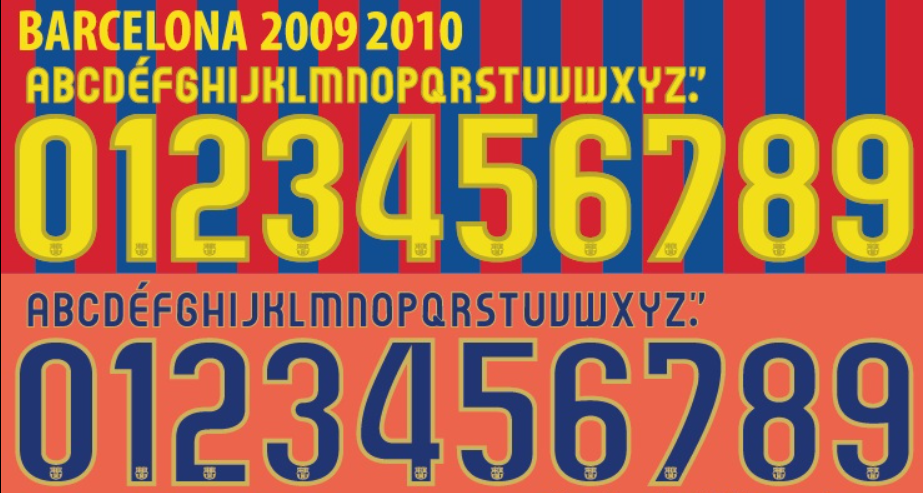
Se existe uma temporada que está gravada na memória de qualquer fã de futebol, é a de 2010/11. Foi o auge do “tiki-taka” de Pep Guardiola, quando o FC Barcelona encantou o mundo. Agora, você pode recriar a magia daquele time histórico com a tipografia oficial utilizada por lendas como Messi, Xavi e Iniesta.
Este arquivo traz a fonte exata desenhada pela Nike para a temporada em que os Culés levantaram a taça da Champions League em Wembley. É um recurso indispensável para colecionadores, designers e personalizadores que buscam fidelidade histórica.
Estilo Visual e Legado
A tipografia criada pela Nike para o ciclo 2010/2011 foge do padrão excessivamente futurista. Ela apresenta um design arredondado, suave e altamente legível, transmitindo a fluidez e a simplicidade do jogo praticado por aquela equipe.
Nos uniformes titulares Blaugrana, a fonte era aplicada em um amarelo vibrante, criando um contraste icônico. Já no uniforme “Away” (verde-azulado), ela aparecia em preto ou branco. Diferente das fontes modernas cheias de cortes e ângulos agressivos, esta fonte tem um charme “clássico-moderno” que envelheceu muito bem, sendo perfeita para projetos que evocam nostalgia e classe.